El 3 de diciembre cumplío 90 años uno de mis directores favoritos: Jean Luc Godard.
Godard es un director suizo-francés que fue parte de uno de los movimientos más importantes del cine francés y a nivel mundial: La Nouvelle Vague.
No voy a negar que es una persona bastante disruptiva, y hasta polémica, pero en sus mejores años supo cambiar a su manera las reglas del cine. Y en los últimos años sigue filmando cambiando las formas y esquemas del montaje.
Quien más quisiera seguir filmando a los 90 años.
Pero hoy quiero compartir no sus peliculas, que amo, si no algo que a mi particularmente me gusta y hasta lo inclui en uno de mis cortos ( Que por cierto pueden ver este fin de semana en el Cine chonflex) y es su tipografia.
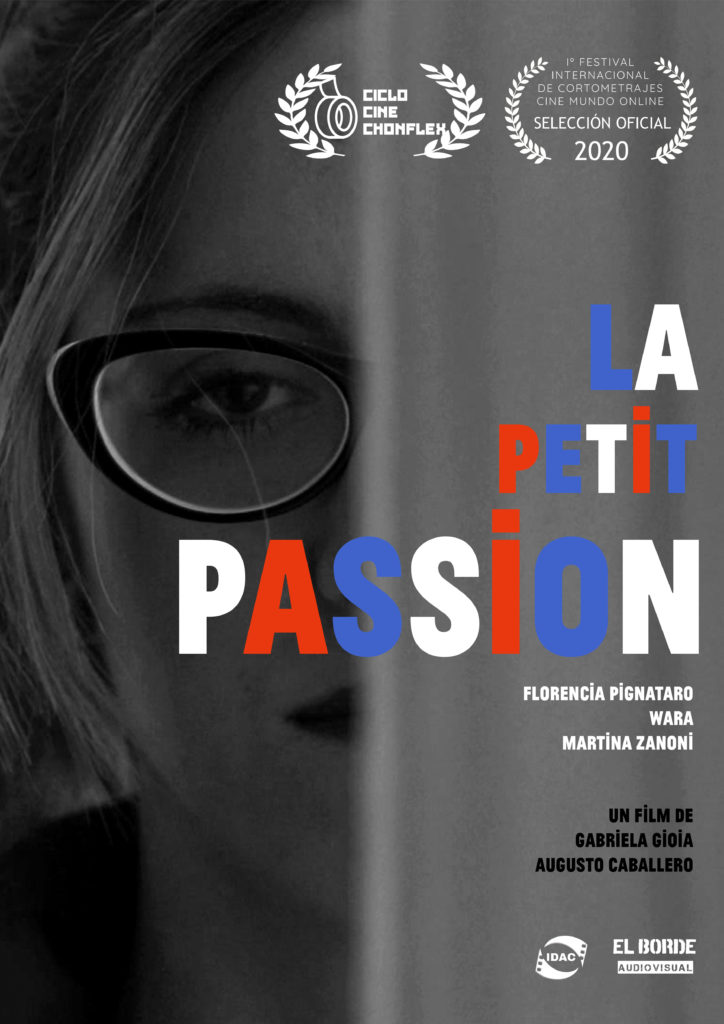
Tipografia homenaje
El 3 de diciembre de 2010, Atelier Carvalho Bernau lanzó una tipografía gratuita para celebrar el 80 cumpleaños de Godard. El tipo de letra se inspiró en las secuencias de títulos de ‘Made in USA’ (1966) y ‘2 ou 3 choses que je sais d’elle’ (1967) de Godard. pero más allá de este homenaje es importante ver la evolucion de los titulos de sus peliculas, que ademas formaban una parte importante en la trama, creando no solo intertitulos sino tambien composiciones de colores basandose en la bandera francesa.
Evolución de las tipografias
Si bien no estudié diseño gráfico, aunque trabaje muchos años como diseñadora en turismo, es algo que me apasiona ver como el diseño acompaña una obra audiovisual.
Creo que es muy importante pensar una pieza desde lo visual, y lo gráfico, acompañando con cada parte que se desprende de la película como si fueran frames en papel u otro tipo de soporte.
– Sin aliento / Al final de la escapada, À bout de souffle, (1960)
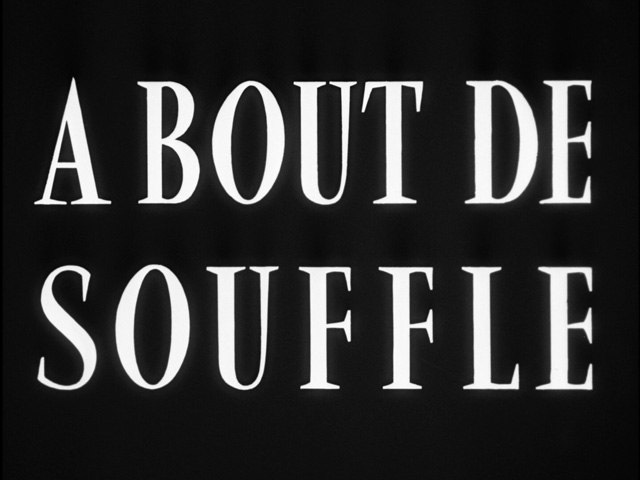
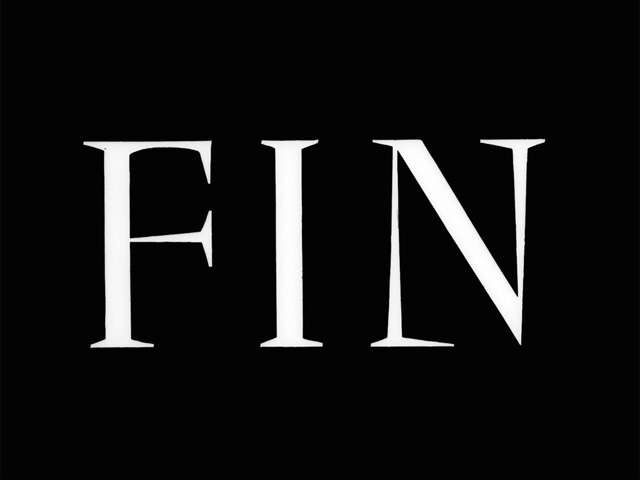
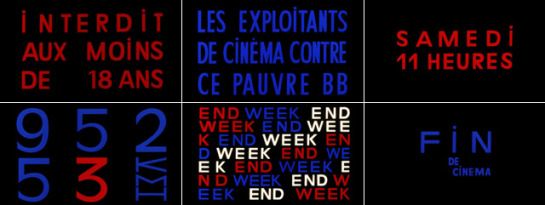
– Una mujer es una mujer, Une femme est une femme, (1961)
– Vivir su vida, Vivre sa vie: Film en 12 tableaux, (1962)
– El desprecio, Le mépris, (1963)
– Los carabineros, Les carabiniers, (1963)
– El pequeño soldado, Le petit soldat, (1963)
– Una mujer casada, Une femme mariée: Suite de fragments d’un film tourné en 1964, (1964)
– Banda aparte, Bande à part, (1964)
– Pierrot el loco, Pierrot le Fou, (1965)
– Lemmy contra Alphaville / Alphaville, une étrange aventure de Lemmy Caution, (1965)
– Made in USA, (1966)
– Masculino, femenino, Masculin, féminin: 15 faits précis, (1966)
– Week-end, (1967)
Creo que Week-end cierra una pequeña etapa en el cine de Godard, los títulos dejan de ser meros representativos para convertirse en intertítulos y disparadores de ideas. Reflexiones al aire que pueden ser tomadas o no.
Atacando con un humor negro a la burguesía, la construcción misma del montaje en el cine, y también la artificialidad misma de la representación riéndose de esta, hasta reflexiona de forma filosófica sobre el arte, la política y la sexualidad.
Por eso termine esta parte de la nota, ya que hay un cambio desde aca en el cine de Godard donde el surrealismo y los mecanismos del montaje irán retorciéndose más.